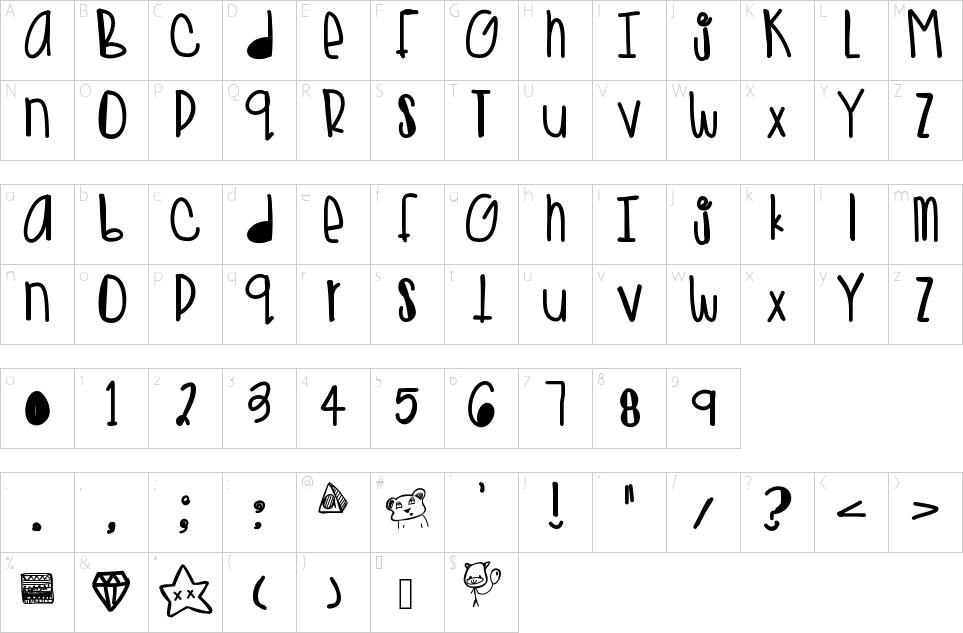
Golden Teddys Font – 1001 Free Fonts – Fonte Grátis
A Golden Teddys Font é uma opção gratuita e divertida para decorar seu design digital com um toque adoravelmente descontraído. Desenvolvida por Des Gomez, esta font garante que sua tipografia brilhe de maneira única e elegante. Com uma variedade de personalidades teddy-bear carinhosamente desenhadas, a Golden Teddys é perfeita para adicionar um toque amigável em qualquer projeto. Sua popularidade crescente se deve ao seu design minimalista e a sua liberdade para criar texturas e formas divertidas que nunca antes haviam sido vistas na fonte gráfica. Atualmente, mais de 2300 vezes esta font foi baixada por criativos interessados em adicionar um toque especial a seus projetos. Seja para cartazes, publicações digitais ou até mesmo para aplicar em mensagens SMS, a Golden Teddys Font é uma opção certeira para quem procura algo novo e divertido no mundo das fontes gratuitas.